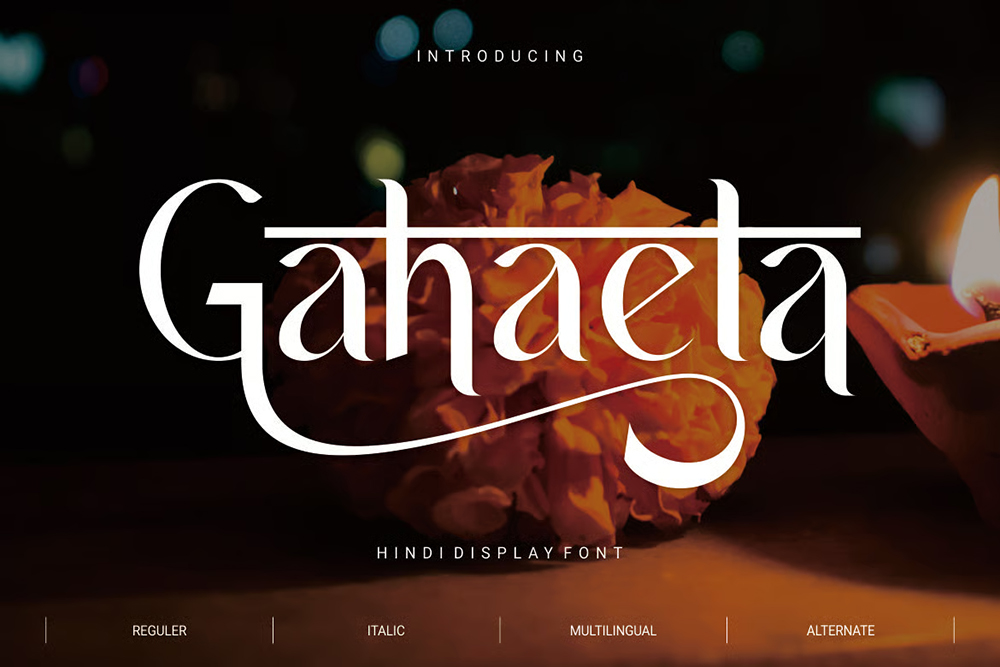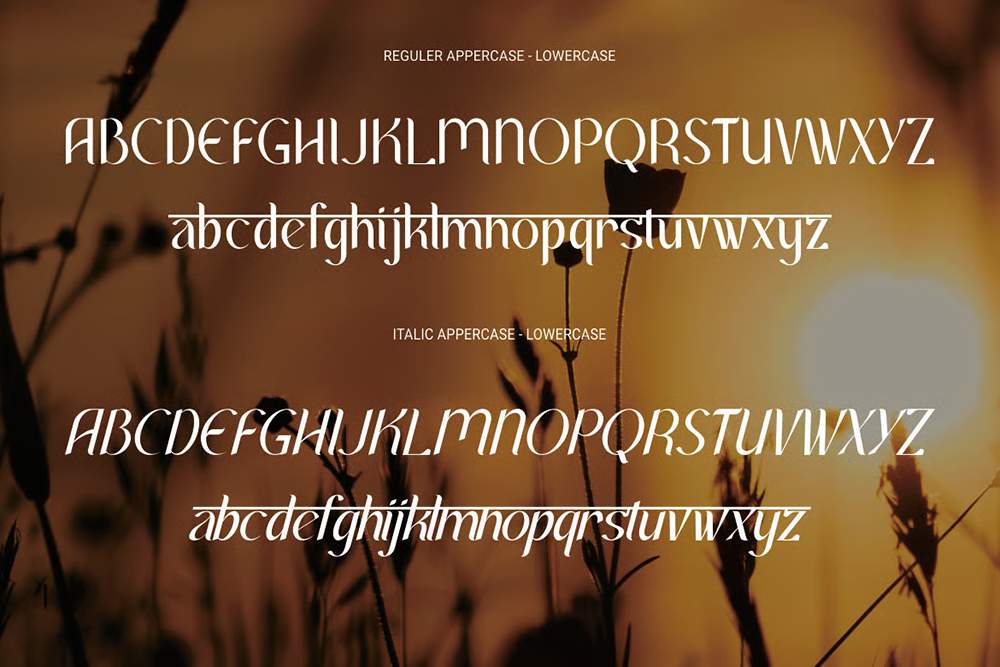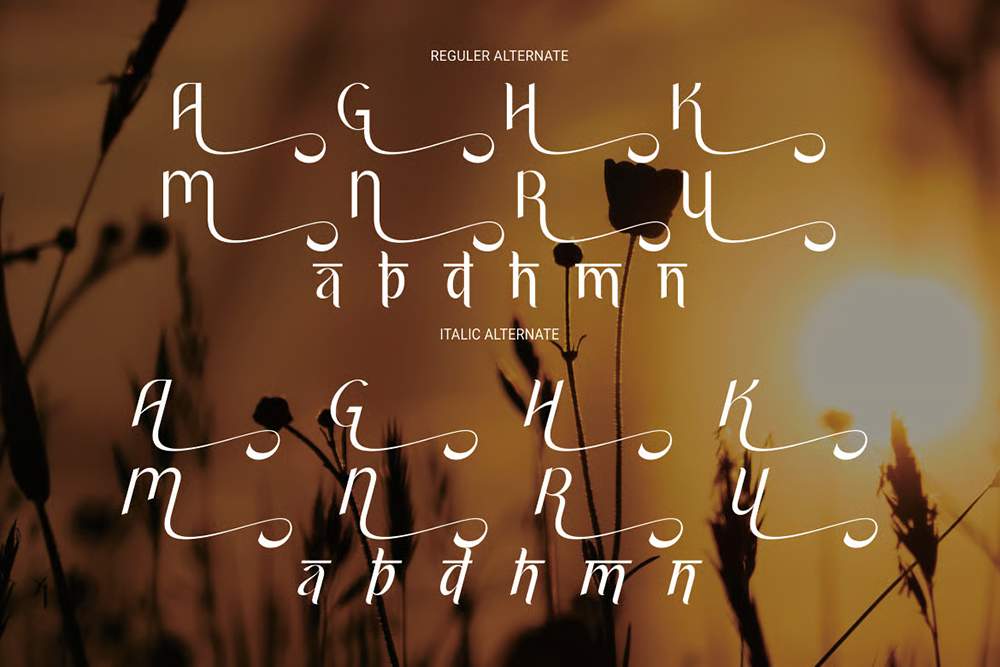
دانلود فونت انگلیسی Gahaela Font
فونت پرمیوم و انگلیسی Gahaela Font یک فونت فشرده جسورانه و مدرن است. Gahaela با خطوط قوی و تأثیرگذار و جزئیات برش منحصر به فرد خود، برای ایجاد عناوین، لوگوها و پوسترهای چشمنواز ایدهآل است. حروف برجسته و برجسته آن، قدرت و اعتماد به نفس را منتقل میکند و آن را برای پروژههایی که نیاز به برجسته شدن و ایجاد تأثیری ماندگار دارند، ایدهآل میسازد. چه برای تبلیغات، مد یا برندسازی خلاقانه طراحی کنید، سبک فشرده و قوی گاهائلا، یک راهحل همهکاره برای افزایش تأثیر بصری ارائه میدهد.
مزایای استفاده از فونت لاتین Gahaela چیست؟